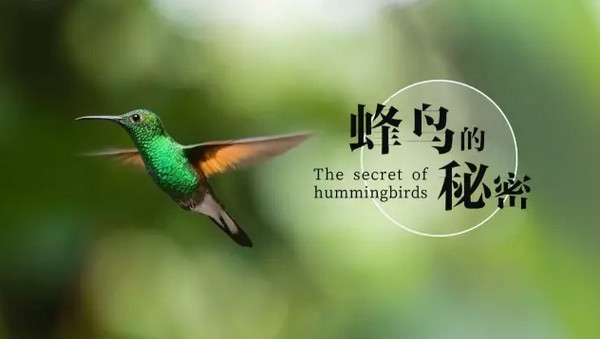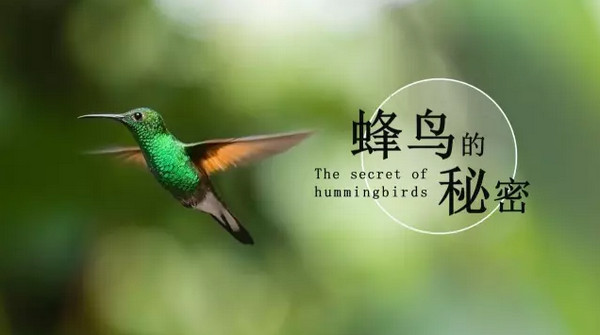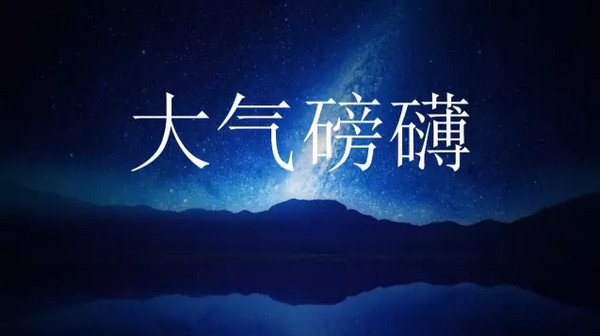
ppt字体怎么不一样 ppt字体怎么保存
你可能没有意识到,你辛辛苦苦设计的PPT发给了老板和同事,但他们打开之后看到的样子居然和你看到的会不一样,丑的不行。
出现这种情况有几个原因:
1)使用的office版本不一样
2)有人使用的是WPS
3)对方电脑里没有安装你使用的字体,你精选的字体全都变成了丑陋的默认字体。
像下面这个样子:
略有文艺范的方正风雅宋字体
结果变成宋体
有气势的汉仪尚巍手书
还是变成糟糕的宋体,气势全无,low的不行。
今天我们就像谈谈这第三种情况——字体的保存。
1) 最好的情况就是对方电脑里也安装了你PPT中使用的字体啦,比如把字体包给到对方,不过这不现实。
2) 你当然可以将特殊字体复制粘贴为图像,这也是很多教程中推荐的方法。
不过这依然有几个问题,首先如果你使用的字体较多,你会不确定到底要粘贴哪些字体。更大的问题是如果使用的特殊字体的页面比较多,要不停的复制粘贴工作量较大。而且这意味着你不能在这些字体中实现一些动画和特效。
3)第3种方法是比较常见的,就是将字体嵌入到PPT中。
以上3种方法都有不足,第三种方法也会遇到例外的情况。
一些字体并不允许我们使用第三种方法将字体保存到PPT里,免费可商用也是非常常用的思源黑体,思源宋体就限制了这方面的权限。
因此,今天介绍的神器就是来破解这个限制的。